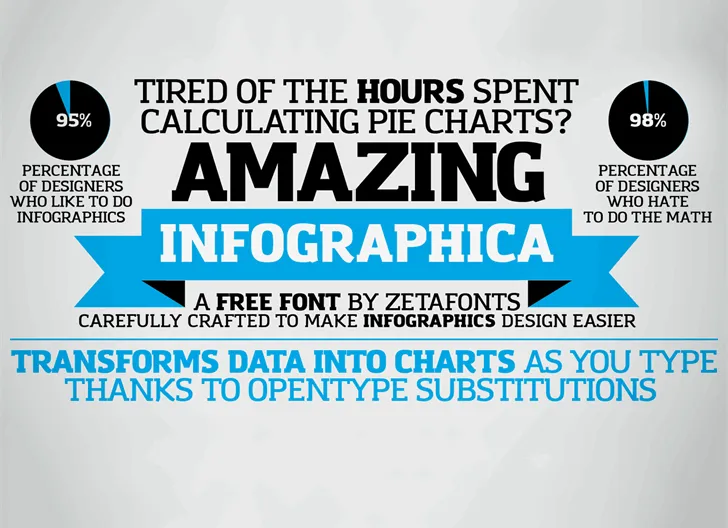
Amazing Infographic@ Font – Download Grátis
Nem sempre é fácil criar infográficos que capturam a atenção do seu público, especialmente quando envolvemos dados complexos como gráficos circulares. Às vezes, pode ser tão desgastante passar horas calculando e desenhando esses gráficos para seus infográficos informativos. Isso é onde entra a font Amazing Infographic@ Font de Zetafonts, uma slab serif que promete facilitar essa tarefa com sua elegância simples e profissional. Esta font oferece um estilo limpo e confortável que pode complementar qualquer projeto gráfico, sem perder a identidade do designer. Ela combina facilmente com linhas geométricas e cores vibrantes para criar infográficos memoráveis e atraentes, tornando-a uma escolha indispensável para quem busca simplificar a criação de seus projetos visuais.